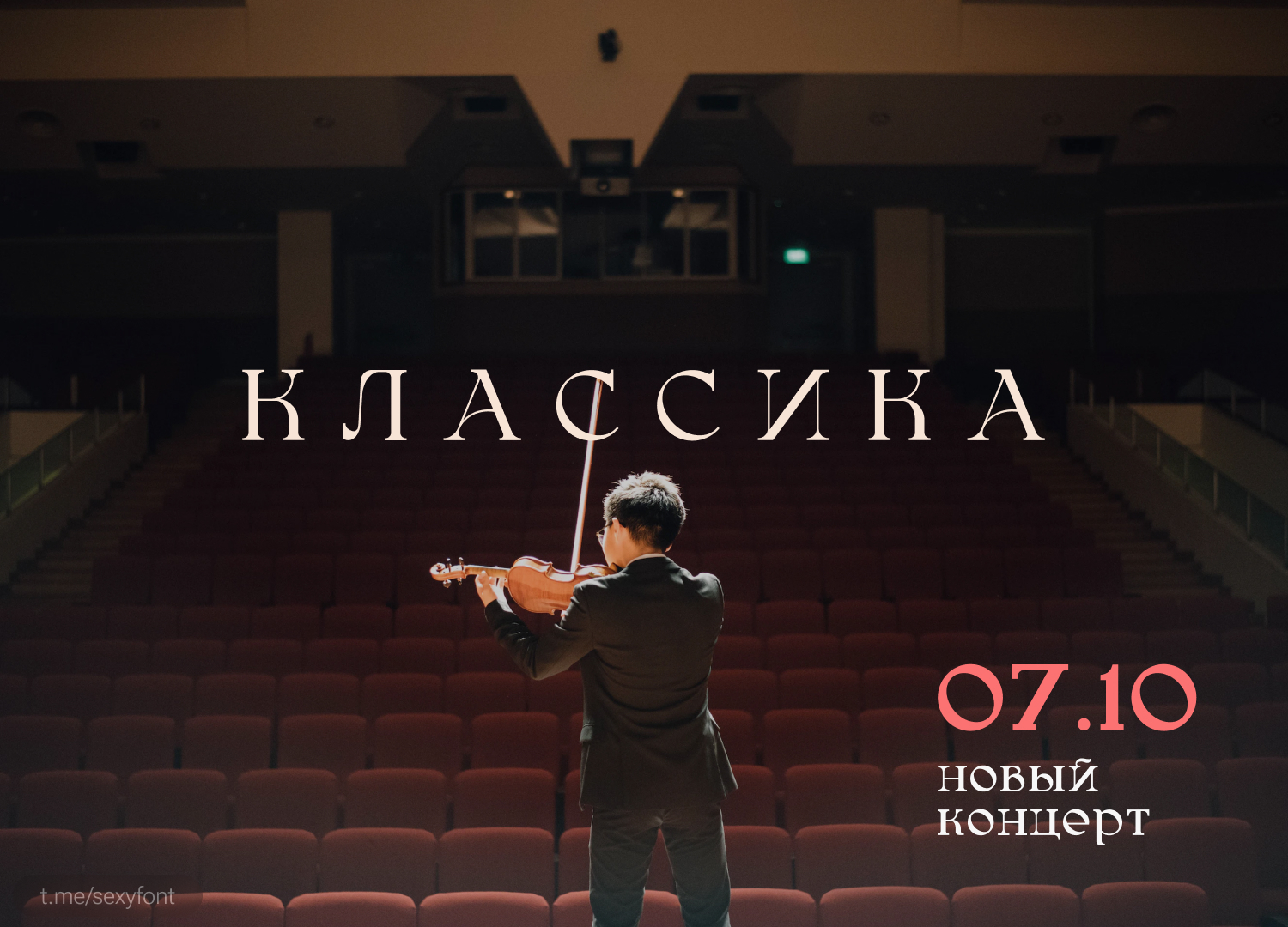
Шрифт bergamasco
Шрифт bergamasco. Акцидентния контрастная антиква. Бесплатно для личного и коммерческого использования. Чего тут рассказывать) Смотри презентацию.